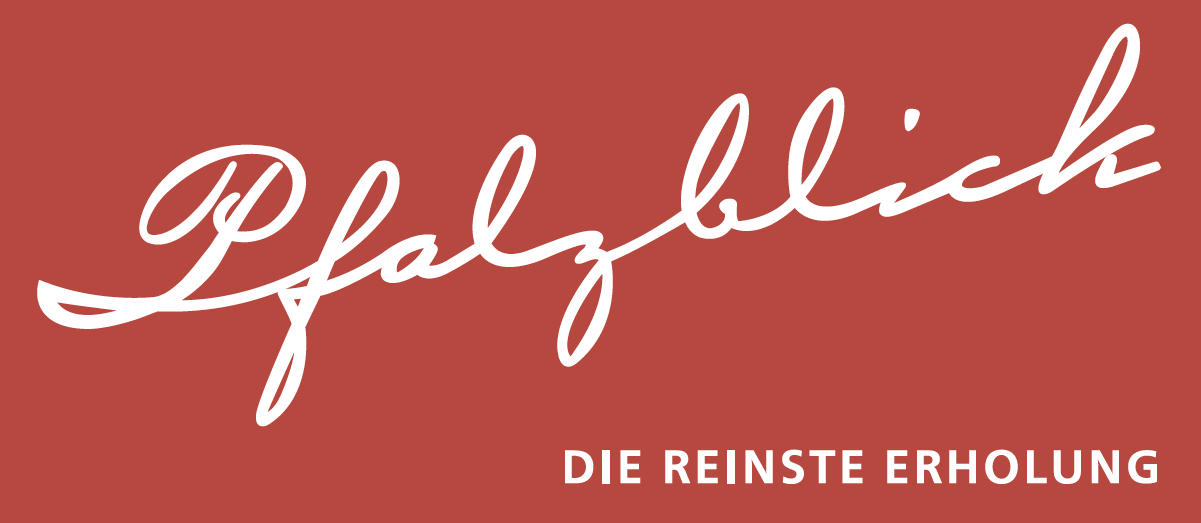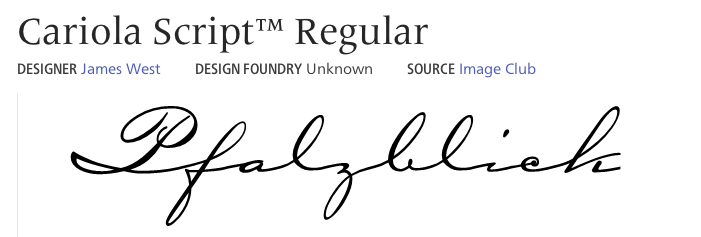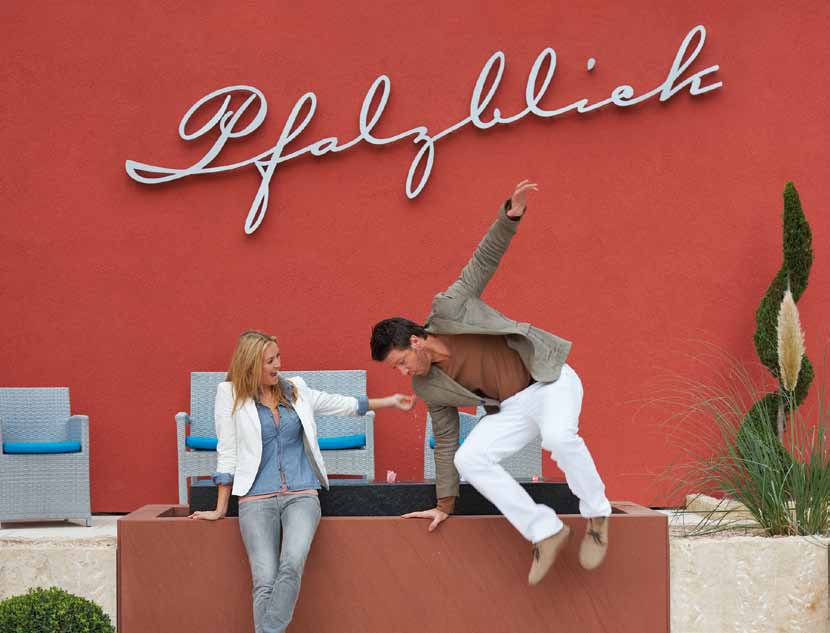
Logoschrift erkennen
Ich würde gerne wissen um welche Schriftart es sich hier handelt .Bin schon seit Wochen am suchen aber finde nix :-((
Der Vorlagenservice …
Nachdem er auch als dreidimensionales Logo auf der Wand prangt, könnte der Schriftzug vom Schilderhersteller für dessen Anforderungen nachbearbeitet und dann vom Hotel für die Werbemittel verwendet worden sein …
Ja, es wurde auf jeden Fall eine Outline drumrum gelegt. (Was der Schrift nicht unbedingt gut tut.)
Meinst du den Schriftzug oder die Schrift? Den Schriftzug könntest du sicher irgendwie aus dem pdf extrahieren. Oder beim Hotel anfordern.
Eine zweite Möglichkeit wäre die Cariola, die hat weniger Unterschiede in der Strichdicke …
Oder ist das nur ein unerlaubter Klon der Carpenter?